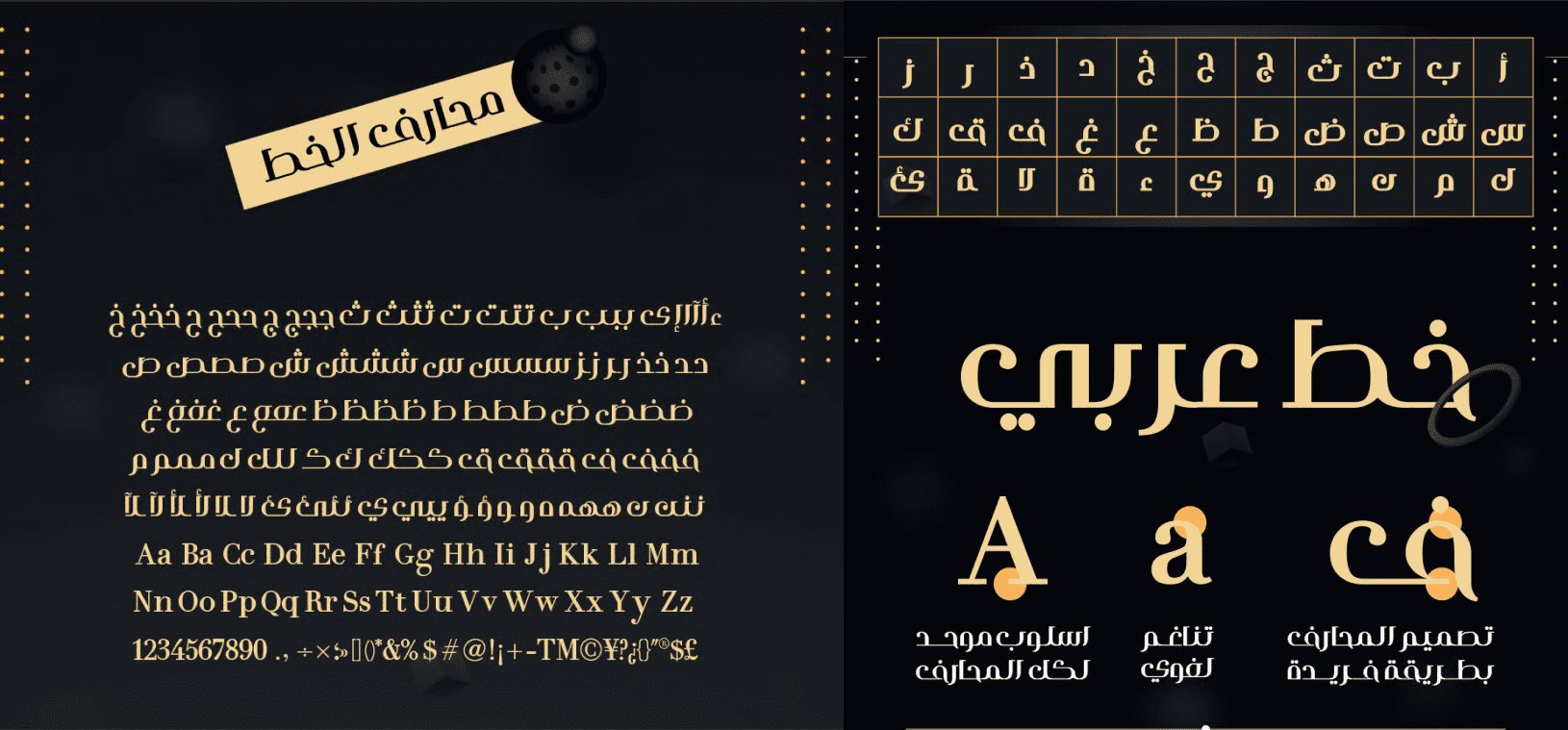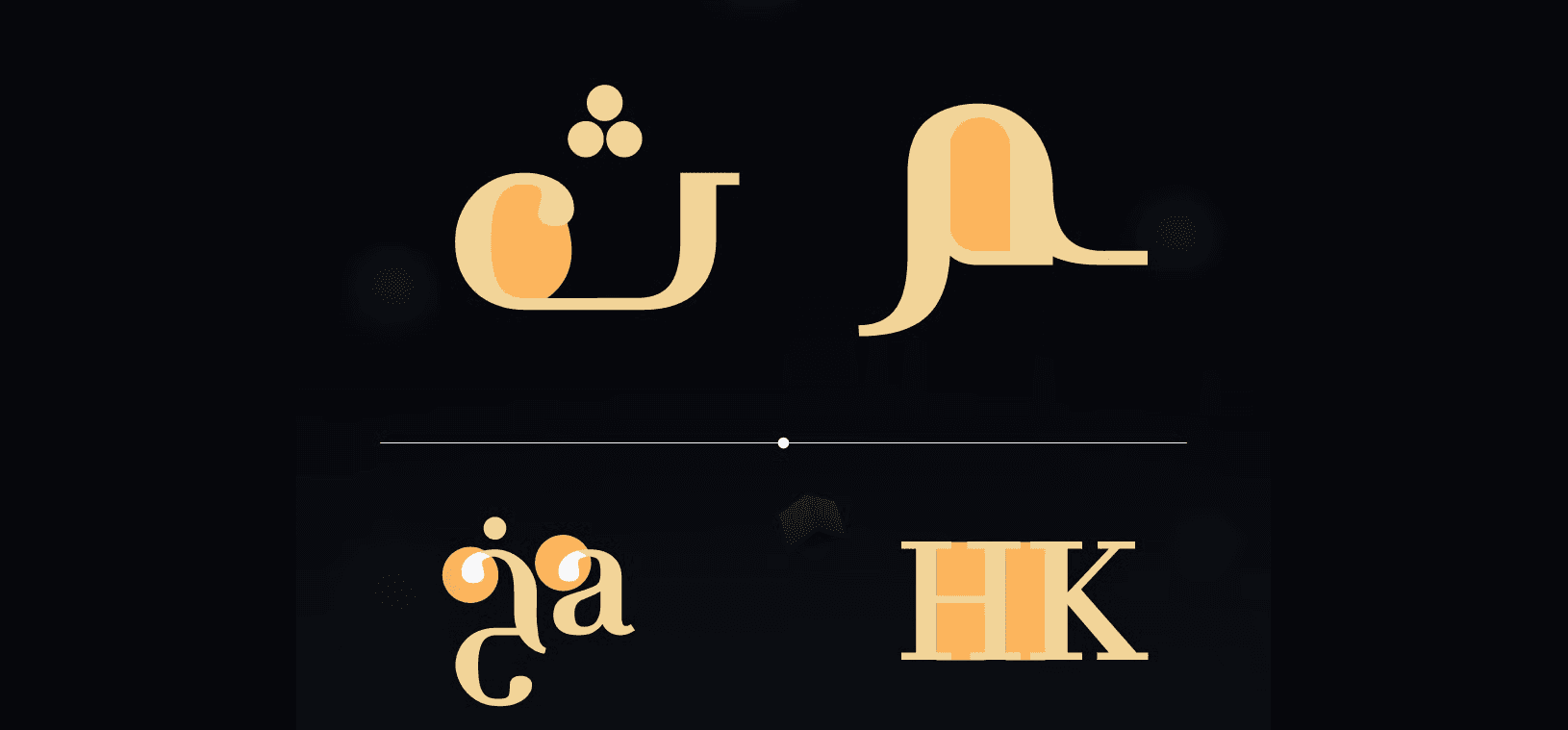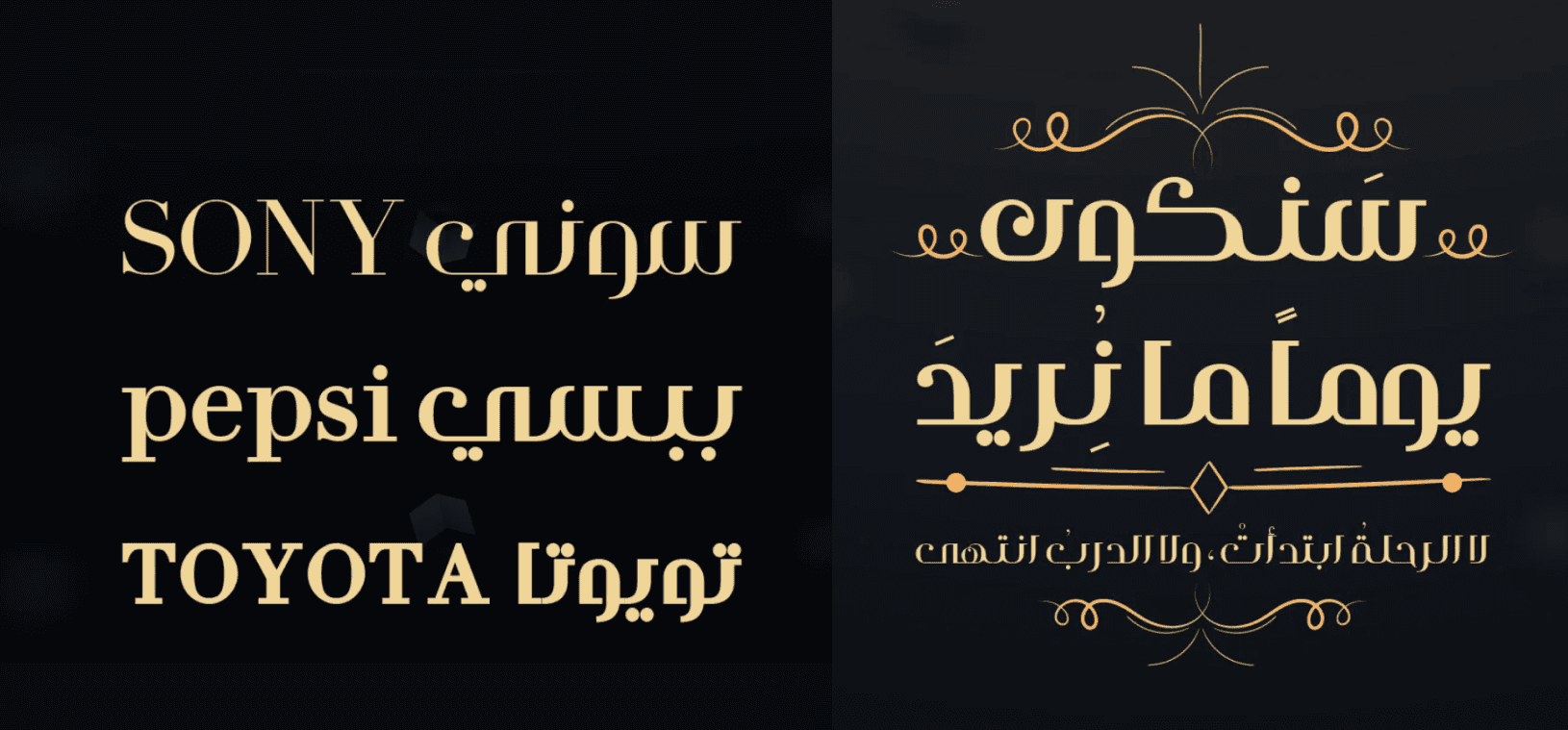
يجمع خط رزَيق 3 بين التصميم الهندسي الصارم والانسيابية البصرية التي تناسب استخدامات الهوية البصرية والشعارات. يتوفر بثلاثة أوزان مختلفة، ويدعم اللغتين العربية والإنجليزية، مما يجعله مثاليًا للتصميمات متعددة اللغات. يظهر الخط بوضوح في الاستخدام الطباعي أو الرقمي، ويمنح العلامات التجارية مظهرًا احترافيًا ومميزًا بلمسة حديثة.